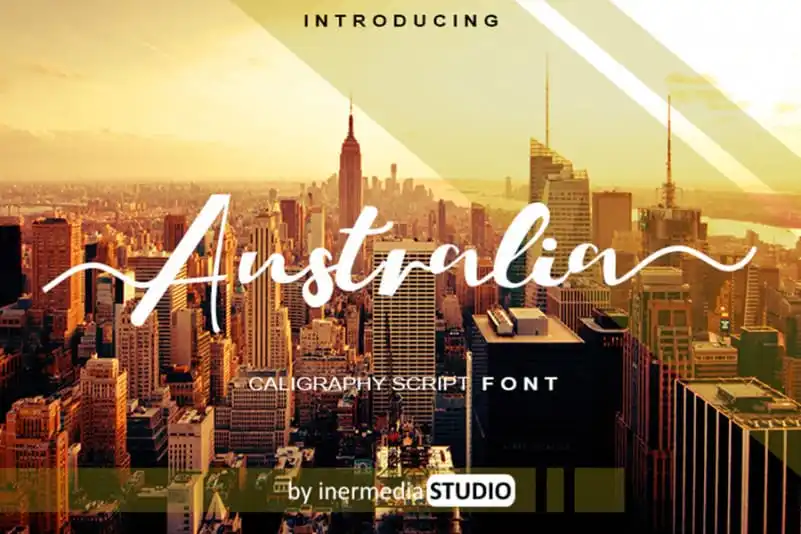
A fonte ‘Australia Calligraphy Font’ é perfeita para quem busca uma mistura elegante de influências antigas com uma sensação atual e fresca. Esta fonte mantém seu estilo clássico de calligrafia enquanto se destaca como uma opção versátil que vai desde assinaturas e títulos até papelaria. Suas formas fluidas e sutilezas sofisticadas oferecem um toque único para seus projetos, tornando-a ideal tanto para quem busca um equilíbrio perfeito entre antigo e moderno, quanto para quem está buscando algo que se destaque na atualidade. Sem dúvida, ela é uma escolha inteligente para designers gráficos que valorizam tanto a essência de uma fonte clássica como o brilho de sua versatilidade contemporânea.